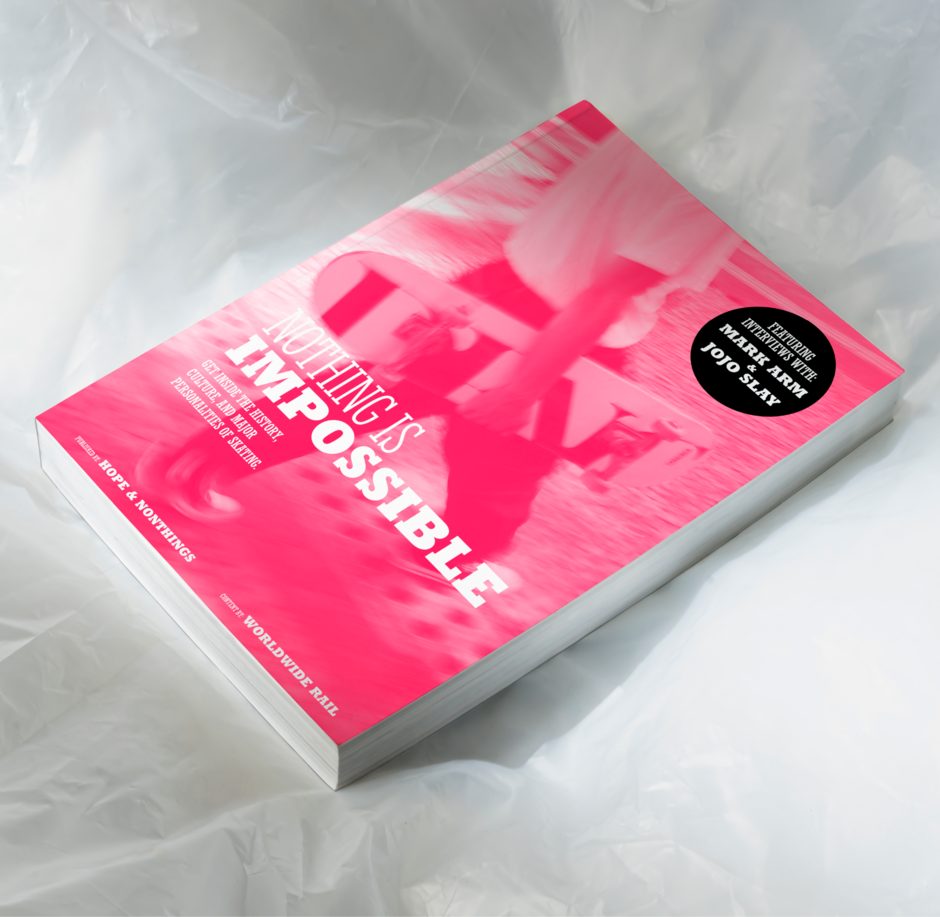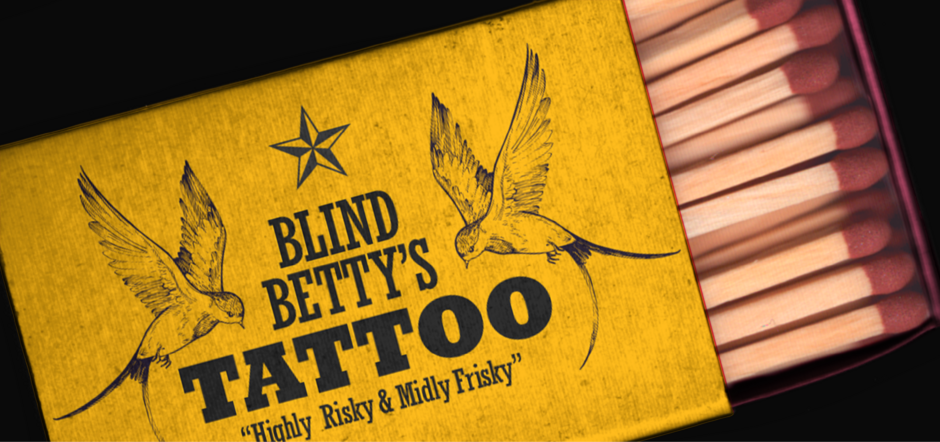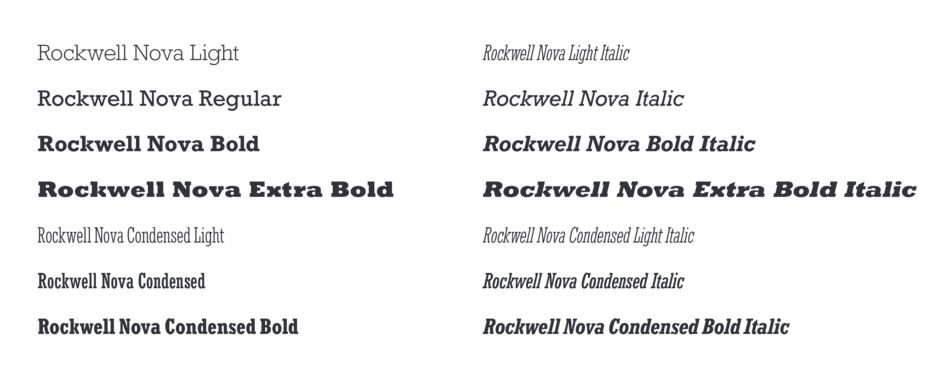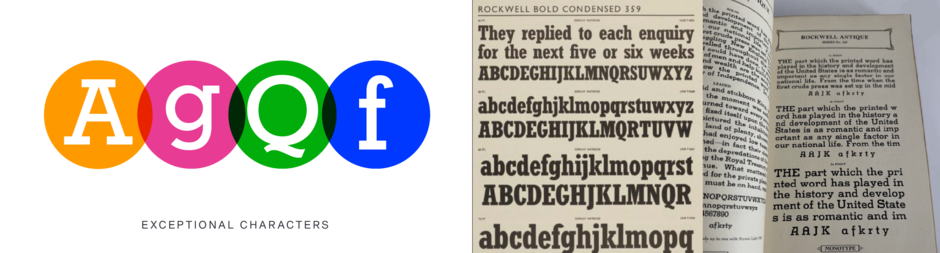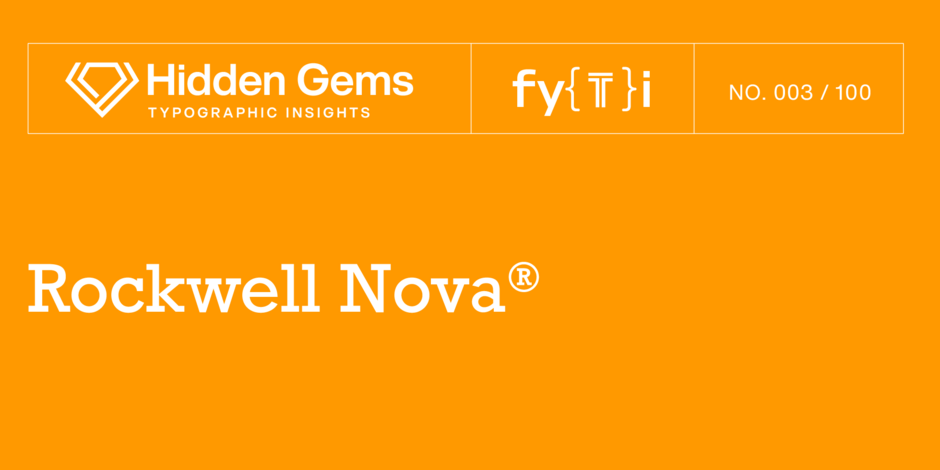
Versteckter Edelstein Rockwell Nova®
Die Rockwell Nova vermittelt ein Gefühl von Ehrlichkeit und Geradlinigkeit. Basierend auf dem ursprünglichen Rockwell-Design ist sie eine anpassungsfähige Schrift, die sich hervorragend für Branding, Überschriften und andere Display-Anwendungen eignet. Die einfachen Formen und die robusten Serifen der Rockwell Nova machen die leichteren Schnitte auch zu einer guten Wahl für kurze Textblöcke sowohl im Druck als auch auf dem Bildschirm.
ANCESTRY
- Die Geschichte der Rockwell beginnt mit dem Londoner Schriftgießer Vincent Figgins, der 1815 die erste erfolgreiche Slab-Serif-Schrift herausbrachte. Es handelte sich um eine reine Versalienschrift namens "Antique", die in drei Größen angeboten wurde. Bis 1825 erschienen weitere Slab-Serif-Schriften, nun mit Kleinbuchstaben.
- In den ersten drei Jahrzehnten des zwanzigsten Jahrhunderts nahm die Popularität von Serifenschriften zu und dann wieder ab, bis geometrische serifenlose Schriften populär wurden. Bald kamen neue serifenlose Schriften auf den Markt, die geometrischen Formen nachempfunden waren. Die Rockwell-Familie, die erstmals 1933 herausgegeben wurde, ist Monotypes kraftvolle Antwort auf diesen typografischen Stil.
- Die Rockwell Nova basiert auf der ursprünglichen Monotype Rockwell-Schriftenreihe, wurde aber sorgfältig auf den neuesten Stand gebracht. Sie ist ein außergewöhnlich haltbares Design, das in der Textgestaltung ein Gefühl von aufrichtiger Ehrlichkeit vermittelt. Sie ist auch ein außergewöhnlich vielseitiges Display-Design, das für Überschriften, Zwischenüberschriften - praktisch überall, wo eine starke typografische Präsenz erforderlich ist - verwendet werden kann.
- Old Style Serif-Designs wie ITC Berkeley Alter Stil, Legacy® Serif, oder Galliard®. bilden einen dynamischen Kontrast zu Rockwell Nova.
- Geometrische Sans, wie z. B. Futura® Jetzt und ITC Avantgarde Gothic® bilden auch einen typografischen Kontrapunkt zu Rockwell Nova.
- Schriftarten wie Metro® Nova und Klassische Groteske erzeugen eine ähnliche Stimmung, bilden aber auch einen guten Kontrast zu Rockwell Nova.
- Der Vorläufer von Rockwell war ein Entwurf namens Litho Antique, der 1910 von der Inland Type Foundry hergestellt wurde. American Type Founders nahm die Schrift in den 1920er Jahren wieder auf, wobei Morris Fuller Benton mehrere neue Schnitte entwickelte. Die Monotype Corporation produzierte ihre Version der Rockwell im Jahr 1933.
- Das große "O" in Rockwell ist ein perfekter Kreis, was bei Serifenschriften selten ist. Die geometrische Konstruktion ist ein Markenzeichen des Designs.